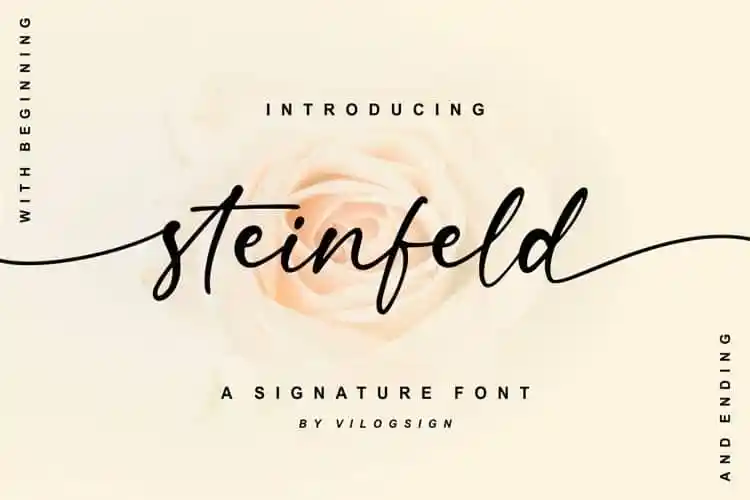
A Steinfeld Script Font é uma nova face script feminina que transforma seus caracteres num movimento elegante ao longo do baseline. Cada letra flui com delicadeza e graça, criando um equilíbrio perfeito entre o tradicional e a inovação. Os designers adotaram cuidadosamente os componentes básicos, incluindo início, meio e fim da palavra, bem como alternativas para criar versatilidade e estilo único e elegante. Esta fonte oferece suporte multilingue para completar suas necessidades de design, tornando-a uma escolha perfeita para criação de marcas, postais, revistas, cartas de cumprimento, citações, logotipos e embalagens. Com seu charme sofisticado e sua capacidade multifuncional, a Steinfeld Script Font é uma fonte indispensável para quem procura um estilo atemporal e criativo no design do comunicado visual.